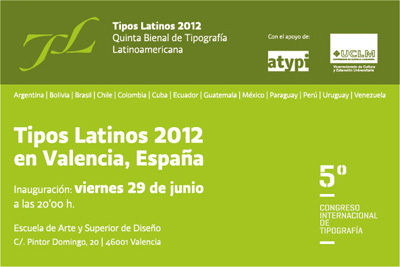
Tipos Latinos, el espacio de encuentro de la tipografía latinoamericana.
La bienal de Tipografía Latinoamericana regresa a Valencia en su quinta edición de la mano de la organización del Congreso de TipografíaTipos Latinos en un evento que se realiza de forma simultánea en varios países y donde Valencia, será la primera sede de la itineraria internacional de la muestra.
La muestra recoge un total de 80 piezas con las propuestas de diseño tipográfico seleccionadas por un jurado de todos los países integrantes del grupo, formados por tipógrafos de Argentina, Bolivia, Brasil, Chile, Colombia, Cuba, Ecuador, Guatemala, México, Paraguay, Perú, Uruguay y Venezuela.
Tipos Latinos incluye fuentes para texto, para títulos, familias completas, diseños experimentales y diseño de tipos no alfabéticos. También se muestran ejemplos de la aplicación y uso cotidiano de estos nuevos diseños que cada dos años enriquecen la oferta tipográfica internacional.